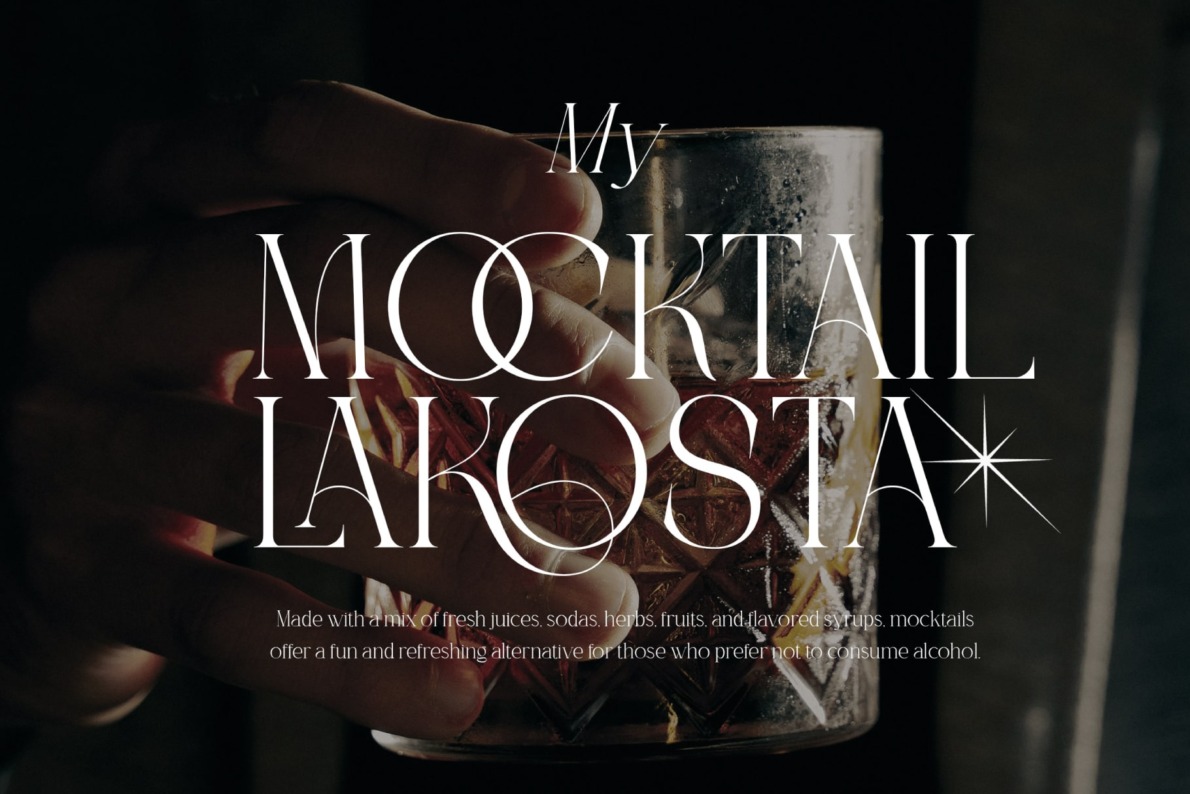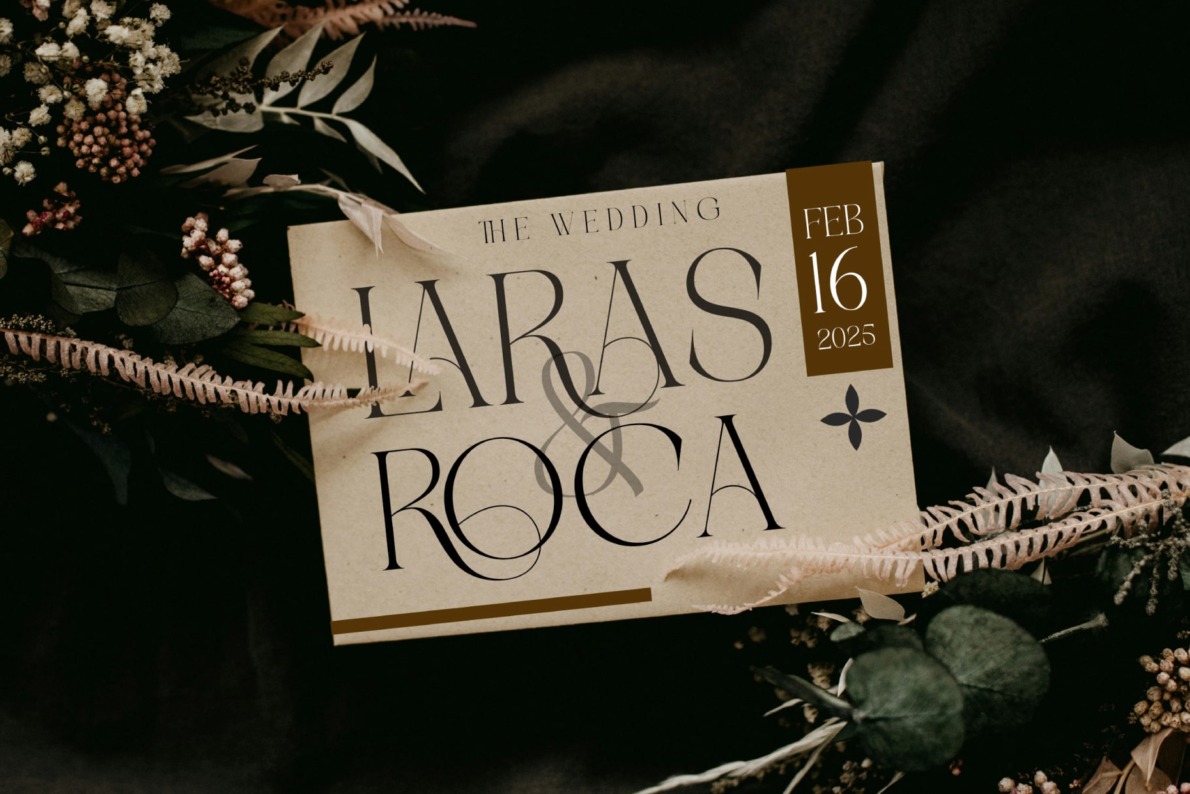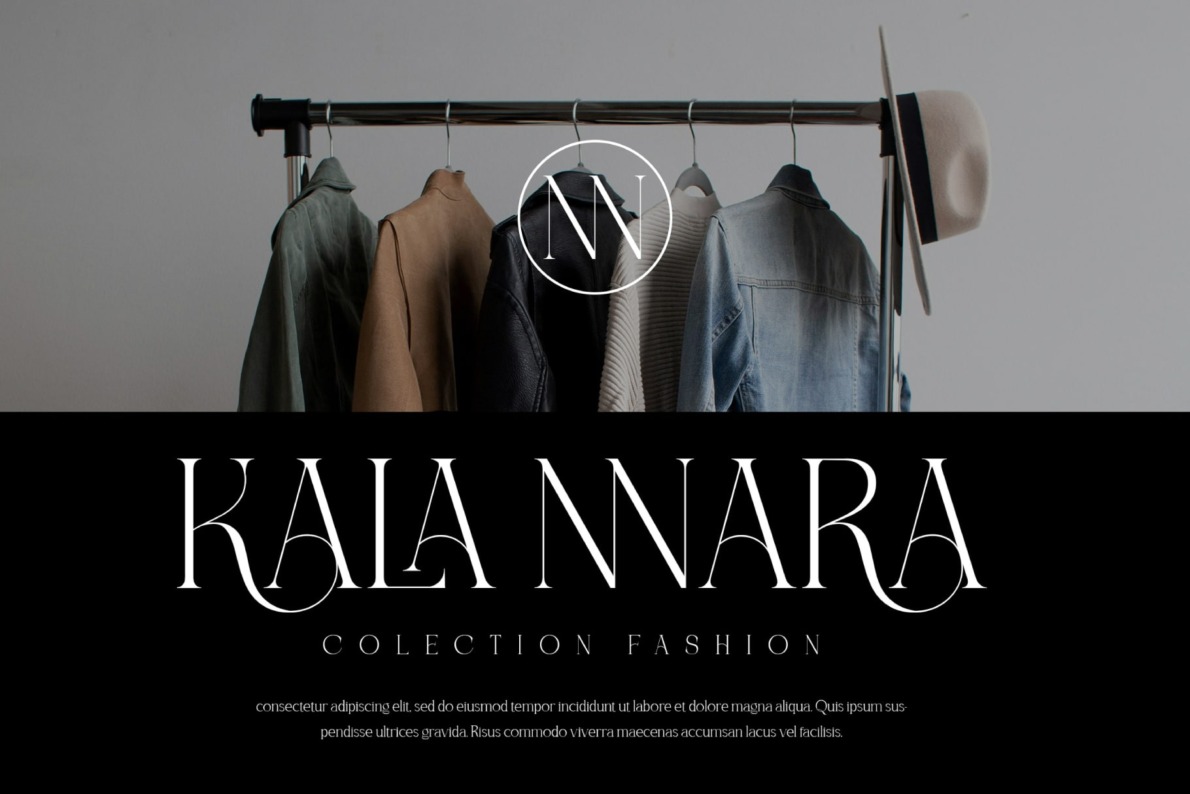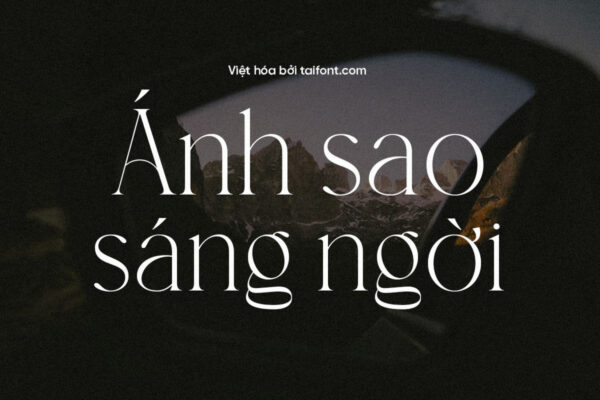
Giới thiệu Font TF Sukari Việt hóa
TF Sukari là một font thanh mảnh nhưng đầy hiện đại và tinh tế. Với thiết kế có chân (serif), font này kết hợp hoàn hảo giữa sự mềm mại, sang trọng, và hiện đại. Các đường nét thanh thoát, rõ ràng giúp font trở thành sự lựa chọn lý tưởng cho các thiết kế yêu cầu tính tinh tế, chuyên nghiệp, và ấn tượng.
Phiên bản Việt hóa của TF Sukari hỗ trợ đầy đủ dấu tiếng Việt, giúp font dễ dàng ứng dụng vào nhiều bối cảnh thiết kế khác nhau. Đây là lựa chọn hoàn hảo cho các thiết kế thời trang, quà lưu niệm, bao bì cao cấp, hoặc bất kỳ ấn phẩm nào cần sự đẳng cấp và chuyên nghiệp.
Nếu bạn đang tìm kiếm một font Việt hóa miễn phí mang phong cách thanh thoát, sang trọng và dễ đọc, TF Sukari chính là lựa chọn tuyệt vời.
Điểm nổi bật của TF Sukari Việt hóa
Việt hóa đầy đủ dấu tiếng Việt.
Kiểu chữ thanh mảnh với thiết kế có chân, hiện đại và tinh tế.
Lý tưởng cho thiết kế thời trang, quà lưu niệm, bao bì sản phẩm cao cấp.
Tạo cảm giác sang trọng, đẳng cấp và dễ tiếp cận
Font TF Sukari Việt Hóa – Font Thanh Mảnh Có Chân Cho Thiết Kế Thời Trang Và Quà Lưu Niệm